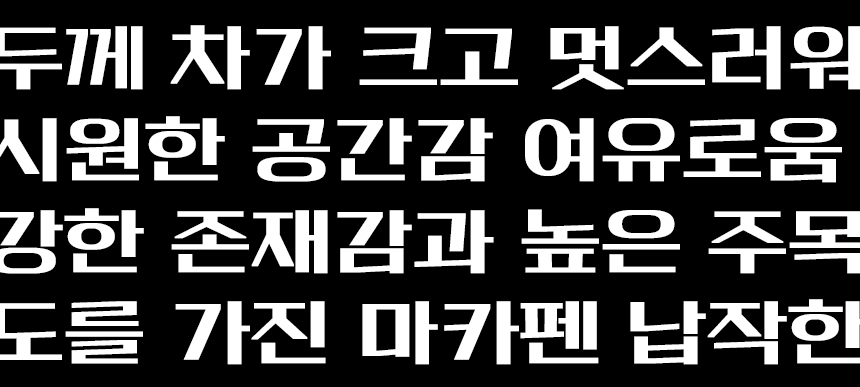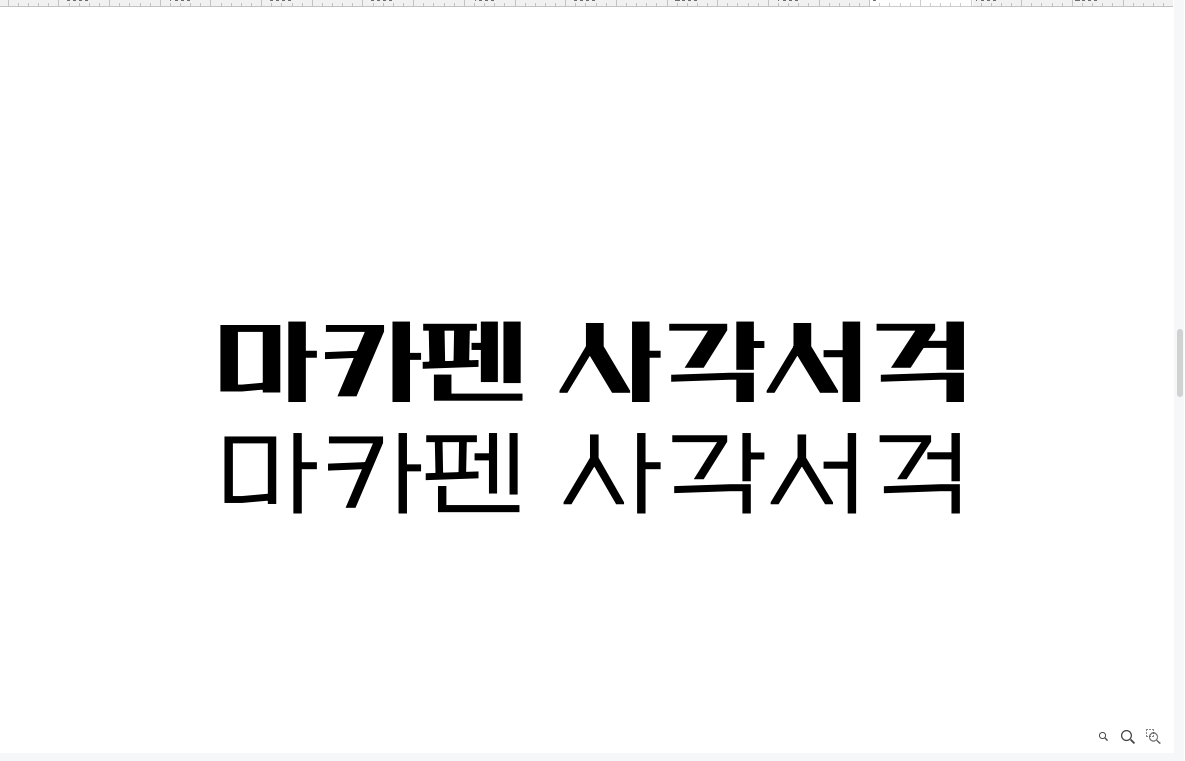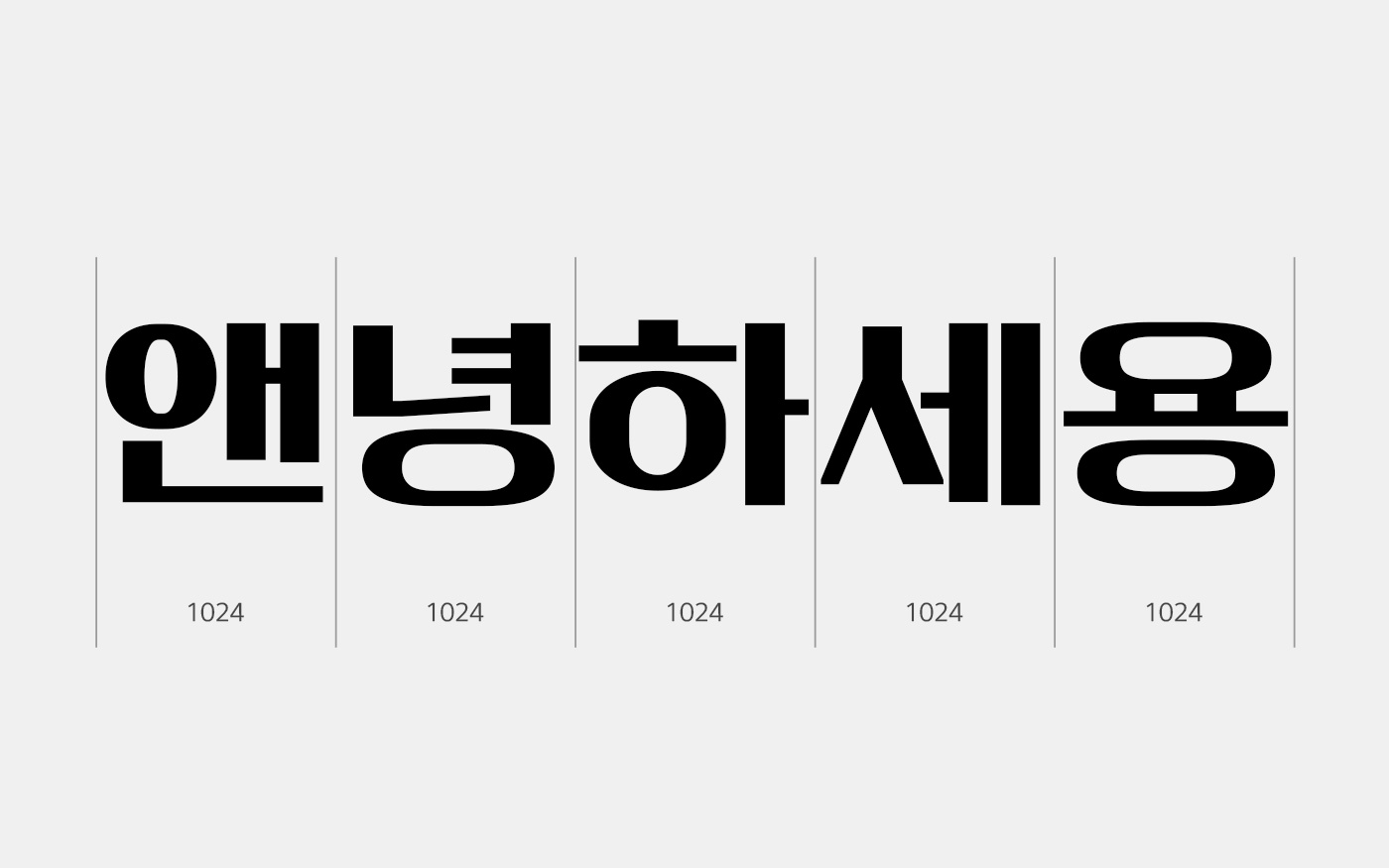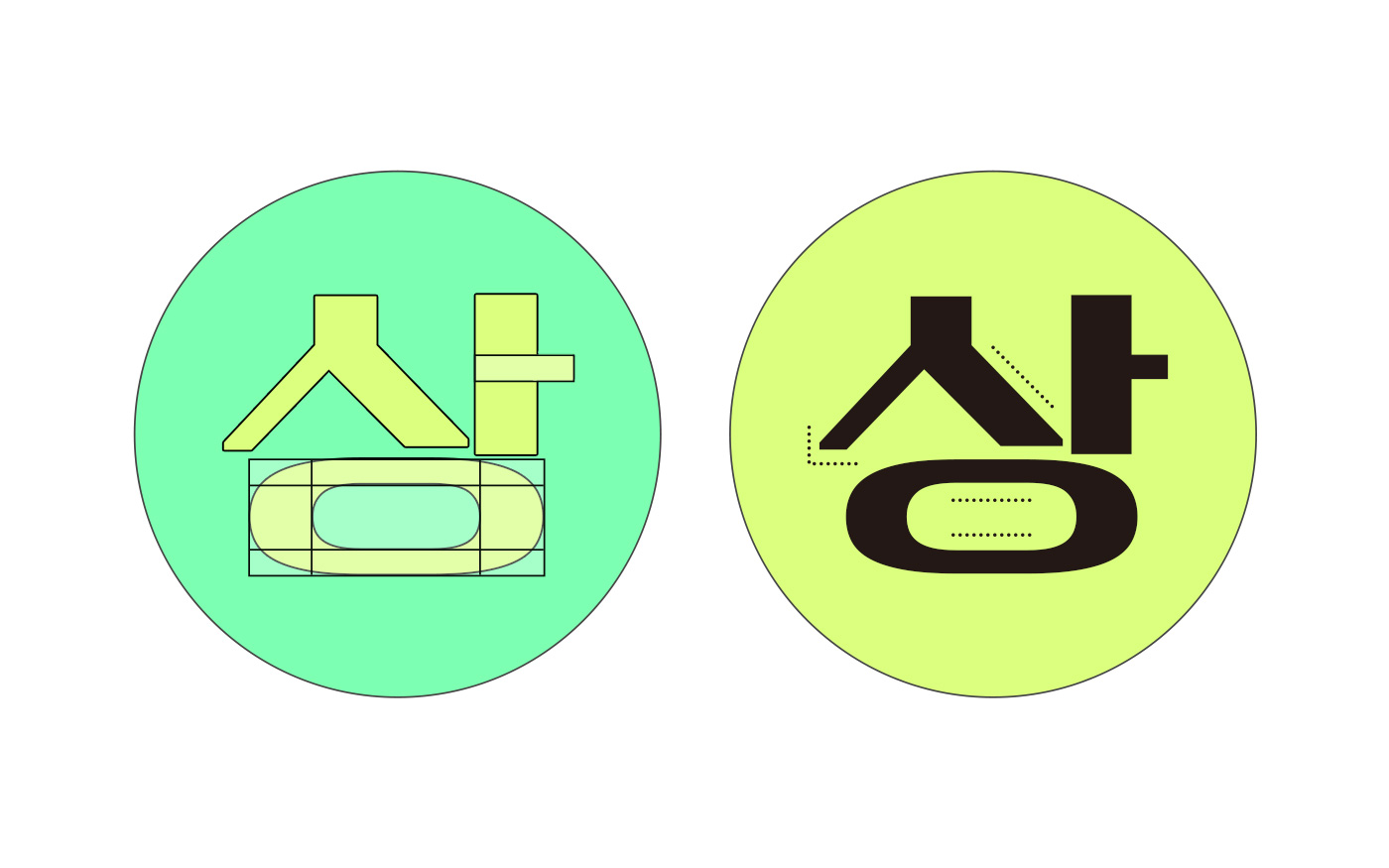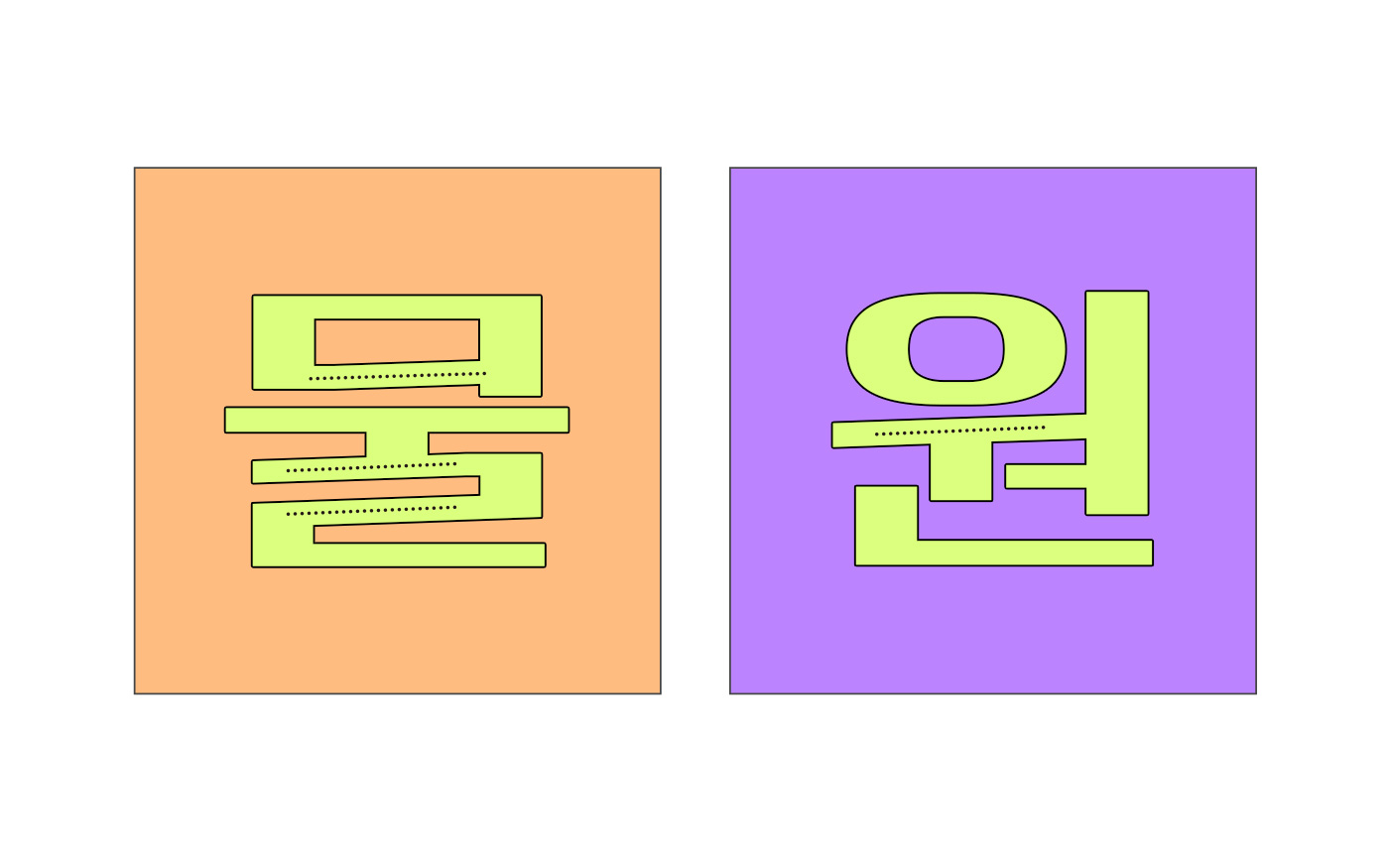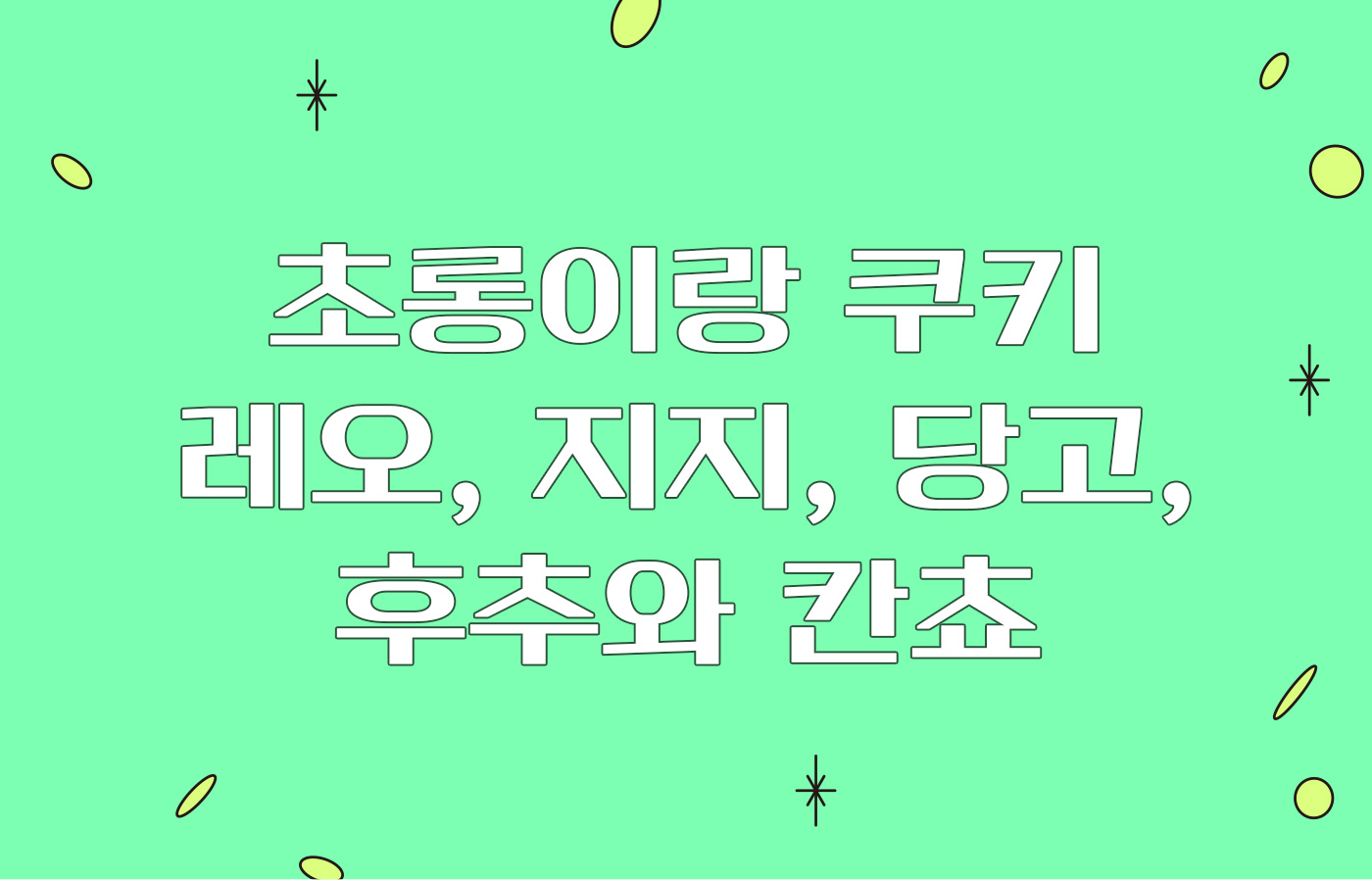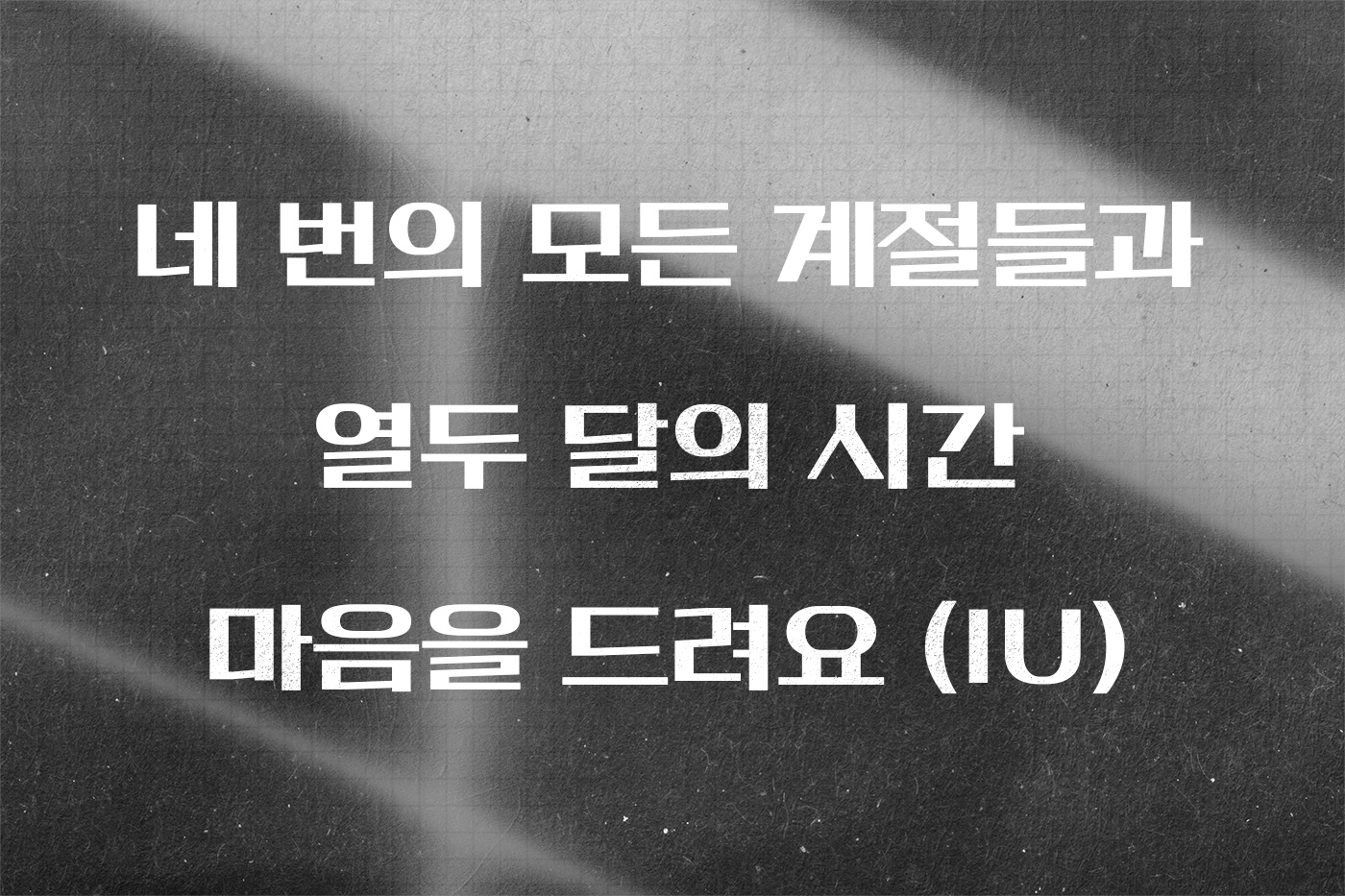
안녕하세요. 따스한 봄이 성큼 다가온 3월, 활기차고 매력적인 신규 폰트 「Rix마카펜」과 함께 인사드려요. 단단한 형태와 리듬감이 느껴지는 Rix마카펜은 두 가지 굵기로 기획하게 되었는데요, 그중 강한 획 대비가 돋보이는 5mm를 먼저 출시하게 되었습니다✨ 이번 폰트를 제작한 유현주 디자이너와의 인터뷰를 통해 Rix마카펜의 탄생 과정을 함께 살펴보겠습니다 :)
코로나라니(눈물) 그런 상황에서도 심혈을 기울여 출시하게 된 이번 신서체, 어떤 폰트인가요?
Rix마카펜은 두꺼운 마카로 쓴 손글씨에서 모티브를 얻어 제작된 폰트입니다. 흔히 아시는 사각닙으로 글을 쓸 때 볼 수 있는 획 대비를 메인으로, 특정 획에서 볼 수 있는 기울기와 직선적인 자소 형태가 특징입니다.
어떤 아이데이션에서 시작되었는지 또 어떻게 제작됐는지 궁금해요.
작년에 담당해서 진행했던 전용서체 프로젝트 중에서 큰 획 대비를 특징으로 한 전용서체가 몇 개 있었는데, RixFont클라우드에는 아직 획 대비가 강조된 폰트들이 많지 않은 것 같아서 기획하게 되었습니다.
제작자가 말하는 활용 꿀팁! 어디에 활용하면 좋을까요?
Rix마카펜 5mm는 아무래도 획 대비가 크고 주목도가 높다 보니 보다 작은 본문용보다는 글자 자체를 크게 보일 수 있는 제목용으로 적합할 것 같습니다. 개인적으로는 큰 효과 자막이나 방송 프로그램 로고로 Rix마카펜을 만나고 싶습니다.
Rix마카펜 웨이트 추가 계획이 있다고 들었어요! 살짝 알려주신다면😊
이번에 출시되는 5mm보다 획 대비가 확연히 줄어든 모습으로 2mm가 업데이트될 예정입니다. 자소 형태나 특징을 5mm와 똑같이 구성할지, 조금 다른 모습으로 구성할지는 앞으로 좀 더 작업을 해보면서 결정해야 할 것 같습니다.
Rix마카펜은 넓고 여유로운 고정 자폭으로 설계되었습니다. 가로 폭이 넓으면서 획의 대비가 강해 시원한 공간감과 더불어 레트로한 아날로그 감성이 느껴지기도 합니다.
두꺼운 세로획의 절반 정도 굵기의 가로 획으로 두께 차가 큰 강한 획의 대비가 특징입니다. 단단하면서 직선적인 자소 형태가 곧고 강인한 인상을 주는 서체입니다.
일부 가로 획에서는 위와 같이 기울기를 주어 적절한 속도감과 의외성을 느낄 수 있습니다. 이는 글자의 인상을 너무 무겁지 않도록 도와주기 때문에 요즘 활용도가 높은 키치하고 캐주얼한 컨셉에도 잘 어울립니다.
동일한 특징을 적용한 영문, 숫자, 특수 기호와의 조합도 조화롭기 때문에 다양한 활용이 가능합니다.
눈에 확 띄는 두껍고 단단한 글씨와 획 대비로 제목용, 헤드라인 폰트로 사용하면 주목도가 높은 서체입니다. 글자의 시원스러운 획과 뉴트로한 인상 덕분에 깔끔하고 귀여운 감성으로 활용하기에도 좋을 것 같아요.!